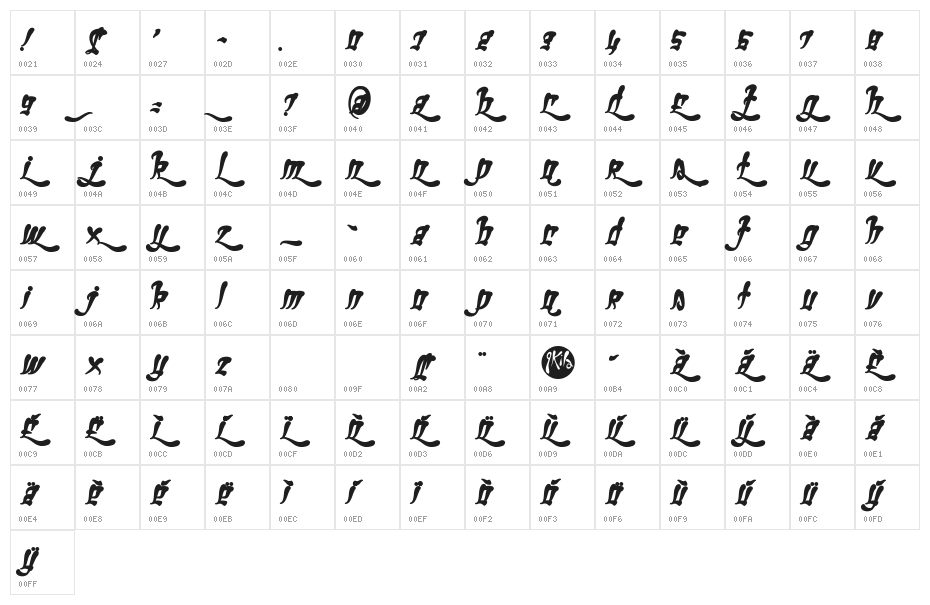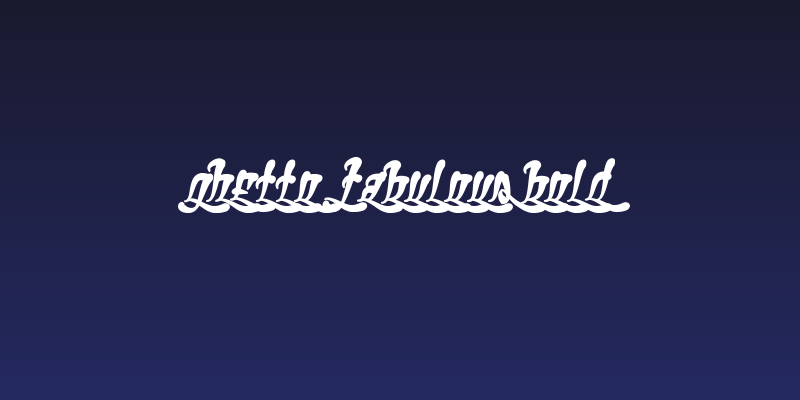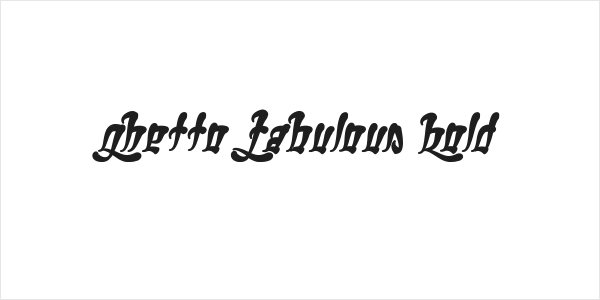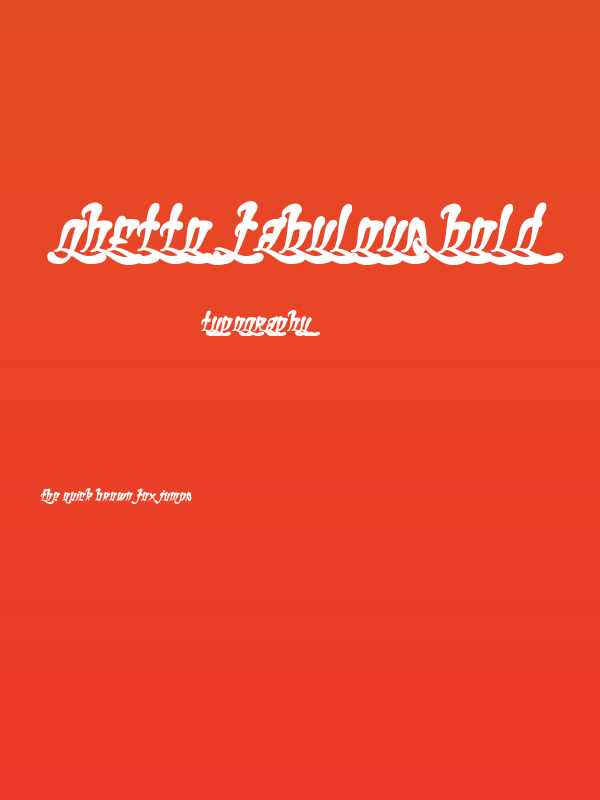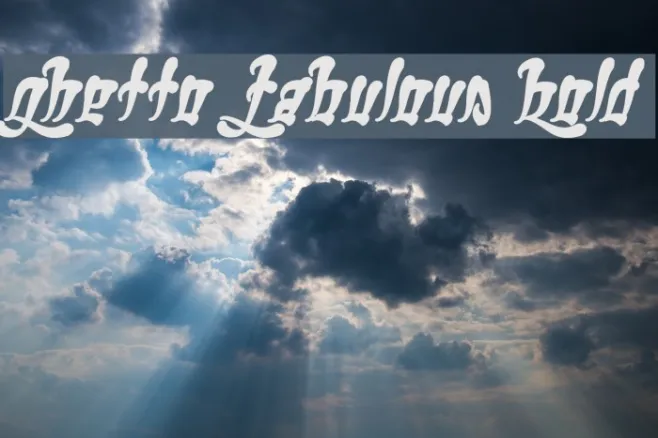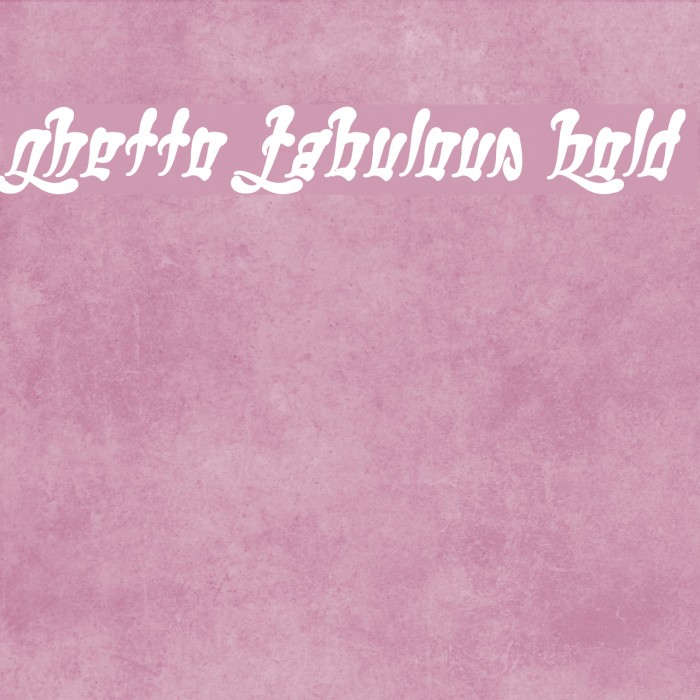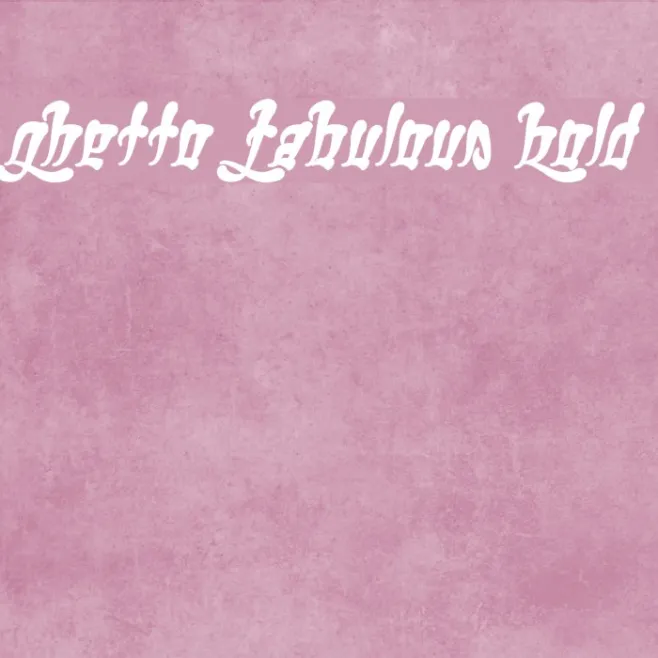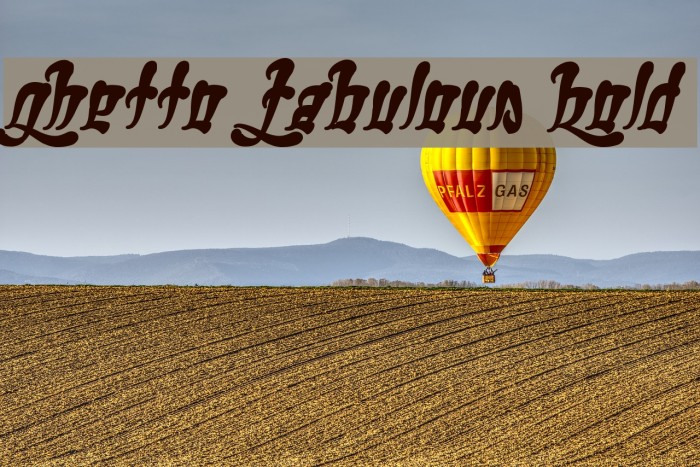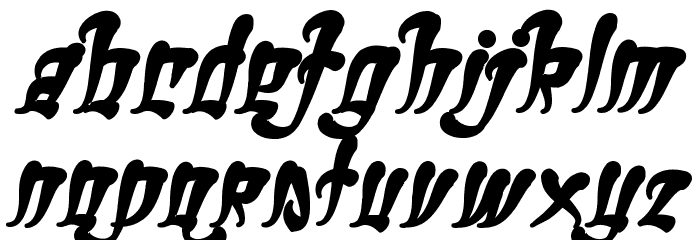
Ghetto Fabulous Bold Font
✎ Script
| Estilo general | Urban, Artistic, Bold |
| Caso de uso | Logos, Headlines, Posters |
| Proyectos propuestos | Perfect for streetwear branding, music album covers, graffiti art, and urban-themed posters. |